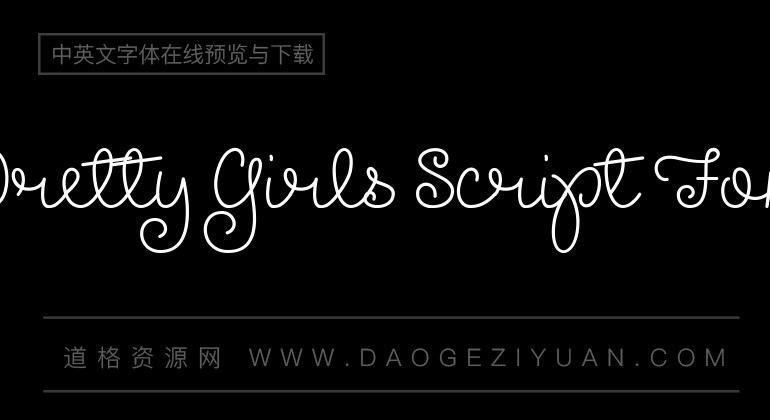
Pretty Girls Script Font
Pretty Girls Script Font 是一种优美而精致的手写字体,它具有一种女性化和华丽的风格。这种字体非常适合用于时尚、美容、珠宝、餐饮等领域的设计项目。 Pretty Girls Script Font 的字母形状流畅,具有一种优美的连笔风格,每个字母都带有一些细节,例如装饰性的弯曲线条和光滑的弧度。此外,这种字体还包含了一些额外的装饰元素,如花卉、心形和星星等,可以为设计项目增添更多的艺术感。 总的来说,Pretty Girls Script Font 是一种非常适合用于女性化和高雅的设计项目的字体,它的细节和装饰元素使得它非常适合用于需要突出个性和时尚感的设计项目。
Pretty Girls Script Font是一款非常不错的手写艺术字体,具有很好的视觉感,适合于文化类的宣传设计、商业类品牌的广告和产品包装设计以及个性化文字排版等较多场景。